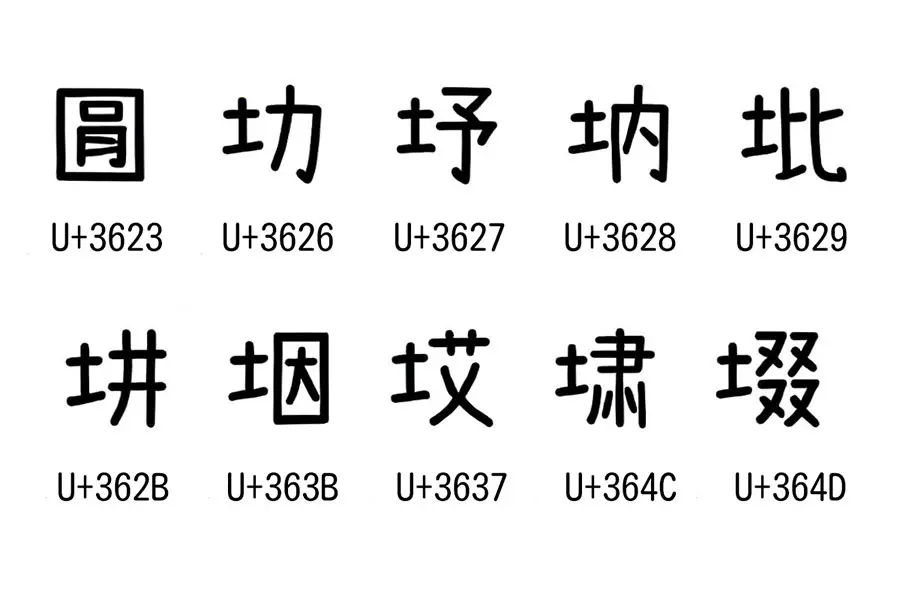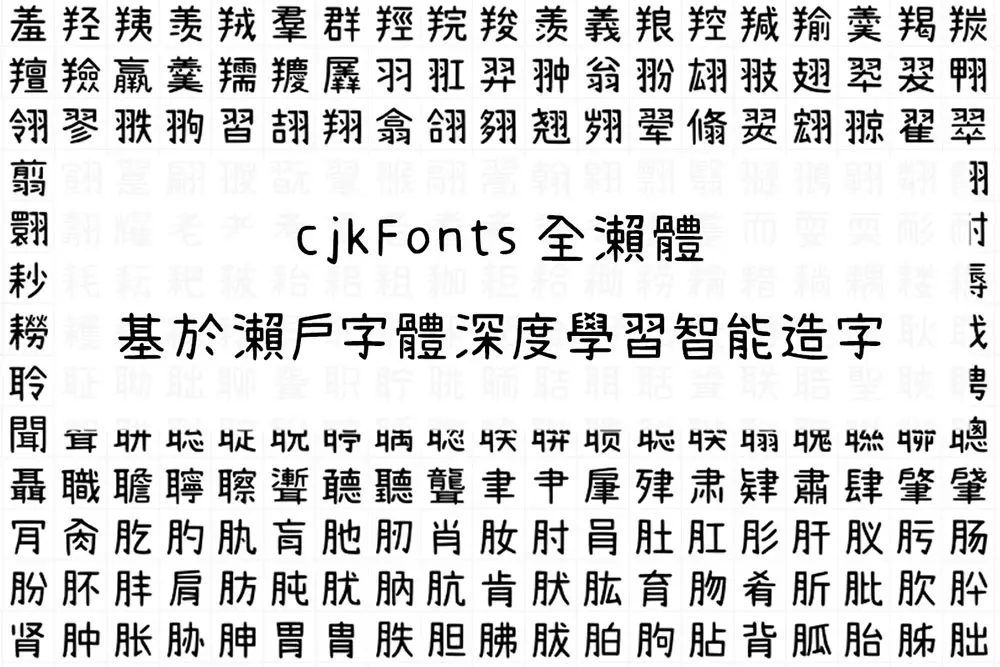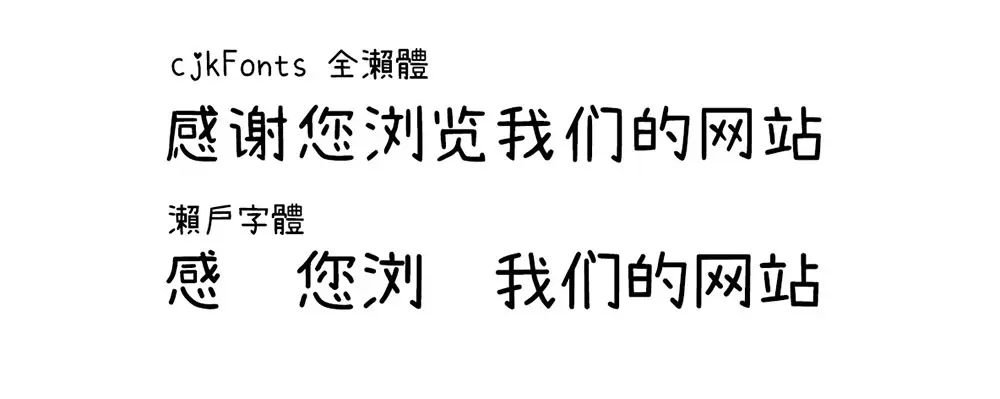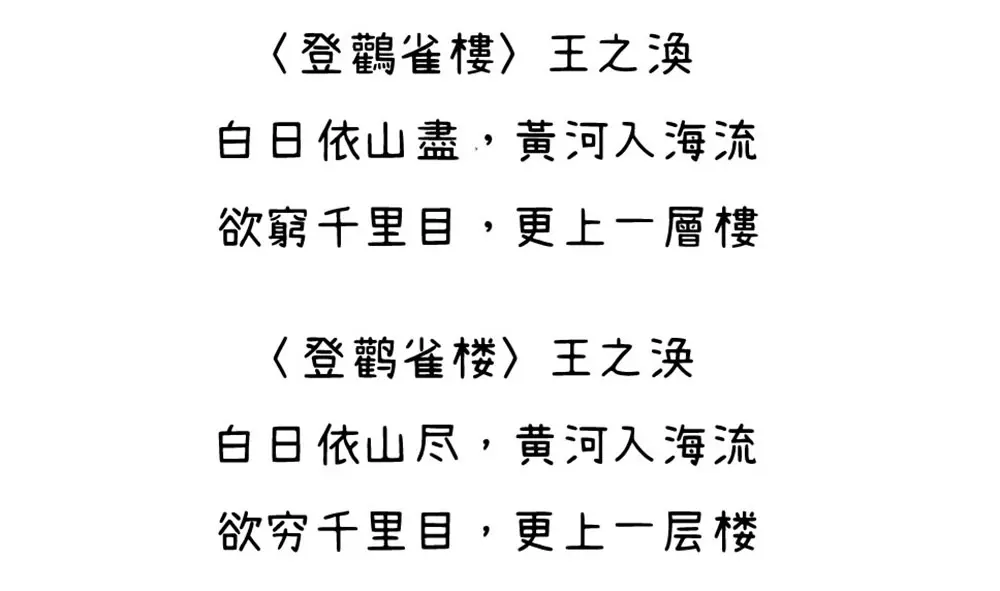
cjkFonts全瀨體是基於瀨戶字體透過深度學習智能造字,產生的字體數量是跟思源黑體相同,所以是全面支持繁簡日韓字體,彌補了瀨戶字體沒有的繁體及簡體字,可以安心使用,不會遇上缺字的情況。
由於是電腦學習了字體的特點及風格後,每個字根據學習後的數據造字,所以字體的風格會跟瀨戶字體有輕微的分別。以下是造字的過程:
1、深度學習訓練:這過程是教電腦學習字體的特點及風格,就像教小明友學寫字一樣。電腦要24小時不停訓練,一般訓練3至4天,初步字體成形。
2、調整字體:訓練完成後,檢視產生的字體,如果有變形的情況,就人手修正。
3、再訓練:修正後的新字體,再加入訓練,重複步驟一,讓機器學習新的字體特點。
4、再訓練:反覆一至三的步驟,當產生的字體達到滿意效果,然後就可以產生全部字體。
5、篩選及調整:產生的字體數量大約4萬2千個字左右,當中會有一些字是變形的,要篩選出來再人工調整,這個步驟工作量是非常大及花費大量時間的。
6、輸出字體檔案:使用軟件組合字體,然後輸出字體檔案(ttf)。
這些全部都是新字體,瀨戶字體沒有這些字的,這些字體是沒有作出任何修正,都是直接電腦造出來,效果都很好。
造出一款字大約要用3至4個月時間,如果人手充足的話,可以縮短至2個月。瀨戶字體的數量已足夠應付一般情況,為何要基於它再造字?
瀨戶字體是一款很可愛的手寫字,在繁體支持上是很足夠的,但是在簡體字上,缺字情況嚴重,很多日常會使用到的字也缺少,我們希望可以補回缺少的簡體字,使繁體及簡體的應用上也可以使用此字體。